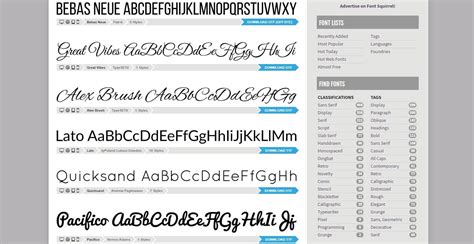
A betűtípusok minden tudásszinten hatékony eszközök - legyen Ön akár kezdő, akár alkalmi felhasználó vagy tapasztalt grafikai tervező. A betűtípusok és a szövegek rendkívül hasznos eszközök számos fotós és tervezési projekthez. Soha nem volt még ilyen egyszerű betűtípusokat hozzáadni a Photoshophoz.
Az Adobe Fonts előnyei
Gyakran használt Photoshop betűtípusok
A leggyakoribb Photoshop-betűtípusok az Arial, a Calibri, a Verdana, a Times New Roman és a Georgia. Ezek mind webkompatibilisnek tekinthetők, mivel szinte minden számítógépen és eszközön széles körben elérhetők. További gyakran használt Photoshop-betűtípusok a Helvetica, a Tahoma és a Trebuchet MS.
Ingyenes Photoshop betűtípusok fotózáshoz és tervezéshez
Ha azzal a feladattal szembesült, hogy szöveget adjon hozzá a fényképezéshez, ezek az ingyenes Photoshop-betűtípusok, amelyeket professzionális fotóretusálók készítettek, nagyon hasznosak lesznek. Ne tedd a képed tetejére az első betűtípust, amivel először találkozol, keress egy figyelemre méltó betűtípust, amely harmonikusan illeszkedik fényképezési stílusodhoz. Az Ön kényelme érdekében a FixThePhoto csapata kiválasztotta a legjobb ingyenes betűtípusokat a Photoshop számára, amelyek alkalmasak különféle típusú fotózásokhoz.
Különböző stílusú ingyenes betűtípusok
- A betűtípus egyszerű, könnyen olvasható betűket tartalmaz, amelyek minden fontos üzenetet közvetítő képhez megfelelőek. Ez a legjobb Photoshop betűtípus, ha azt szeretné, hogy a szöveg kiemelkedjen.
- Még egy áttekinthető betűtípus, apró további serifekkel a széleken ebből a betűkkel. Ez az egyik legjobb professzionális betűtípus, amelyet kissé hosszúra rajzolt betűk jellemeznek.
- Ez tekinthető az egyik legnagyobb, teljesen olvasható ingyenes betűtípusnak a Photoshop fotózáshoz logóihoz.
- Ez egy ingyenes betűtípus-generátor, amely lehetővé teszi, hogy szövegét stílusos betűtípusra formázza közvetlenül a böngészőben. Ha ezt a betűtípust alkalmazza a szövegére, akkor biztosan felkelti a figyelmet.
- Ha fel kell hívnia a figyelmet a szövegre, vagy jobban láthatóvá kell tennie, ez a betűtípus tökéletes lesz. Az ebből a legjobb fonts Photoshop listához tartozik.
- Ez az egyik legnagyobb, kézzel rajzolt ingyenes Photoshop betűstílus.
- Kiváló serif betűtípus azok számára, akik fotózás logó betűtípusokat keresnek.
- Ez az egyik legismertebb ecset legjobb Photoshop betűtípus.
- Nem tévedhetsz ezzel a serif betűtípussal, ha arra van szükséged, hogy a szöveg egészen egyszerűnek és minimalistanak tűnjön.
- Az ebből this font név mindent elmond - az ebből állandó alakú betűk, amelyek enyhén merésznek tűnnek.
- Ez az egyik legmegfelelőbb ingyenes betűtípus természet- és tájképekhez.
- A geometrikusan hosszú rajzolt betűket ebből a betűtípusból vékony és egyenetlen ecsetvonások egészítik ki. Ha ingyenes betűtípusokat keres a tervezők számára, ez az egyik közülük.
- Még egy egyedi betűtípus, amely úgy néz ki, mintha ecsettel festették volna. Ez az egyik legegyszerűbb és olvasható ingyenes Photoshop betűtípus.
- Ez az egyik legelegánsabb Photoshop aláírási betűtípus. Ez a betűtípus kiváló aláírási betűtípusként szolgálhat.
- A logók legjobb betűtípusai közül ez a leginkább figyelemfelkeltő. Ha fényképezési vízjel-betűtípusokat keres, nézze meg ezt.
- A betűtípust a palatábla írás ihlette. Az ebből a betűk belső részeit vékony egyenetlen vonalak borítják. A betűtípus nagyszerű kiegészítője a kézírásos betűtípusok listájának.
- Egy másik fantasztikus, kézzel rajzolt ingyenes betűtípus a Photoshophoz. A betűtípus a fúziós ebből vastag és vékony vonalakat, valamint finom íveket tartalmazza.
- Ez egy nagyon minimalista és könnyen olvasható betűtípus, tiszta vonalakkal. Ez a betűtípus hihetetlenül ötvözi a félkövér betűket finoman ívelt élekkel.
- Ez az egyik legkiválóbb ingyenes fényképezési betűtípus.
- Ez egy kiváló ingyenes betűtípus az Adobe Photoshop számára, amely kissé hasonlít a Linterashoz. A tervezőknek szánt ingyenes betűtípusok közül ez minden bizonnyal a legszokatlanabb.
- A betűk valódi, kissé olvashatatlan kézírásnak tűnnek. Ha univerzális betűtípust keres, akkor ezt is kipróbálhatja. Ez a legjobb fotós betűtípusok egyike.
| Georgia | Webkompatibilis, széles körben elérhető |
| Helvetica | Gyakran használt |
| Tahoma | Gyakran használt |
| Trebuchet MS | Gyakran használt |